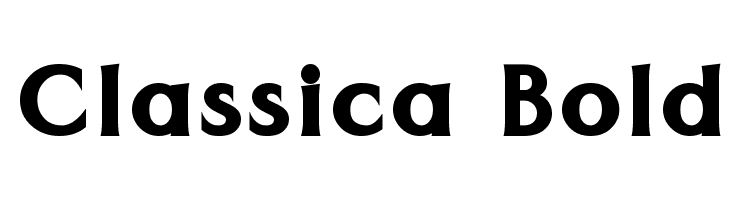
A bold, italicized font with a futuristic and dynamic style.
A modern, geometric font with a digital and futuristic aesthetic.
A playful, hand-drawn font with a textured and whimsical style.
A pictorial, silhouette-based decorative font inspired by paper-cut art.
A modern sans-serif font with clean lines and balanced spacing.
A bold, geometric font with sharp angles and high contrast.
A bold, blocky font with a vintage yet modern appeal.
A classic serif font with medium weight and balanced readability.
A bold, dynamic serif font with a modern twist and high contrast.
A futuristic and angular font with a sleek, geometric design.
A playful, hand-drawn font with rounded, uniform strokes and a whimsical touch.
A bold, modern sans-serif font with an oblique style and consistent thickness.
Transit-inspired display font with bold, geometric symbols.
A bold, angular font with a fantasy-inspired, dragon-like design.
A fluid, cursive script font with elegant strokes and a natural handwriting style.
A bold, modern sans-serif font with geometric shapes and clean lines.
A bold, geometric font with a futuristic and expanded design.
A clean, modern sans-serif font with a light weight and uniform stroke width.
A bold, flowing script font with a modern and elegant style.
A whimsical, cloud-themed decorative font with bold, playful characters.
A modern, geometric font with a linear and rhythmic design.
A bold, playful font with a modern and dynamic style.
A playful, rounded font with bold, smooth curves and a friendly appearance.
A bold, cursive script font with elegant, flowing strokes.
A playful, handwritten font with fluid, slightly irregular strokes.